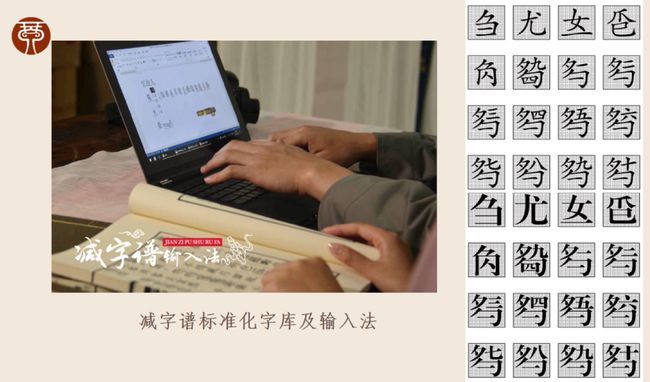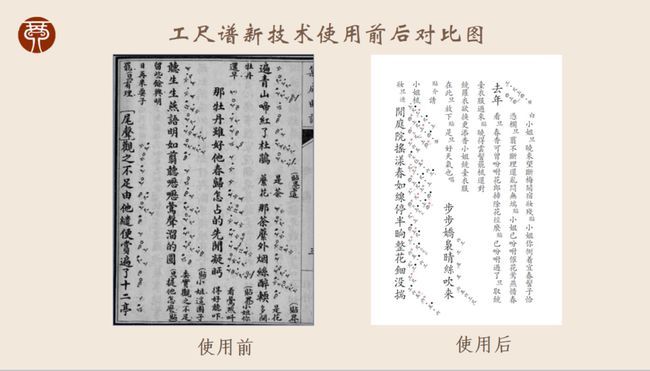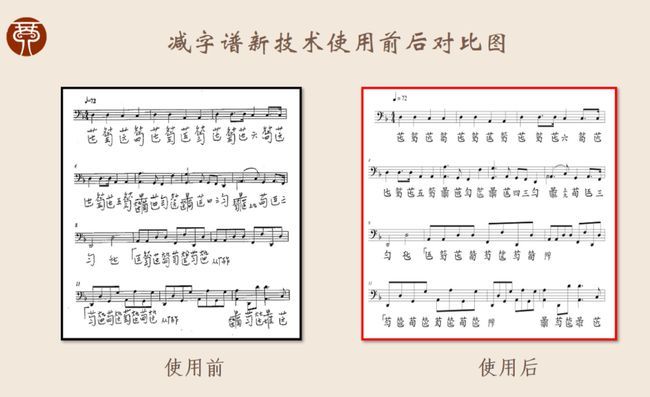
《红楼梦》里有这样一个片段:贾宝玉去潇湘居看林黛玉,发现她在看书,书上的字他一个也不认识,就说:“妹妹越发长进了,看起天书来了。”黛玉看的“天书”其实是古琴减字谱。
减字谱和工尺谱是中国古代使用范围最广、历史最悠久的记谱法,古琴、琵琶、古筝、箫、昆曲等中国传统音乐都是以这两种记谱法为载体传承的。工尺谱因用工、尺等字记写唱名而得名,属于文字谱的一种。由唐末琴家曹柔创立的减字谱,由文字谱简化而来。这种记谱法使用减字拼成某种符号记录左手按弦指法和右手弹奏指法,是一种只记录演奏法和音高,不记录音名、节奏的记谱法,“字简而义尽,文约而音赅”。
由于西方记谱法传入,中国传统古谱逐渐失去昔日辉煌,在一些领域甚至面临失传困境,留下了大量未破解的音乐文献典籍。打谱者就像翻译家,要把琴谱中的符号翻译成有节奏、有旋律、便于现代人识别的谱子。4月15日,“中国传统古谱打谱中心”在上海印刷集团“传庐”正式揭牌,该中心由上海音乐出版社与上海印刷(集团)有限公司合作,将以现代化技术手段对流失海外、散落民间的中国传统古谱进行打谱、制作、出版。
过去10年,上海音乐出版社在减字谱与工尺谱数字化录入、保存与出版方面取得一系列突破性成果,在上海印刷技术研究所的支持下,先后研发了古琴减字谱输入法、减字谱字库、工尺谱排版软件等,获“第六届中国数字出版博览会创新技术奖”、上海高新技术成果转化等荣誉,并陆续推出《雷激古琴系列——入门琴谱》《雷激古琴系列——经典琴曲》《古琴基础教程》《古琴入门教程》等出版物。
“中国传统古谱打谱中心”成立后,将对以减字谱、工尺谱为代表的古谱文献进行数字化转换、存储,同时利用融媒体技术予以再现,并聚焦海内外珍稀古谱及当代名家的今译版乐谱,陆续推出系列出版物,重建古谱的音乐信息,让记录在文物典籍中的中华音乐在当下重新响起来。